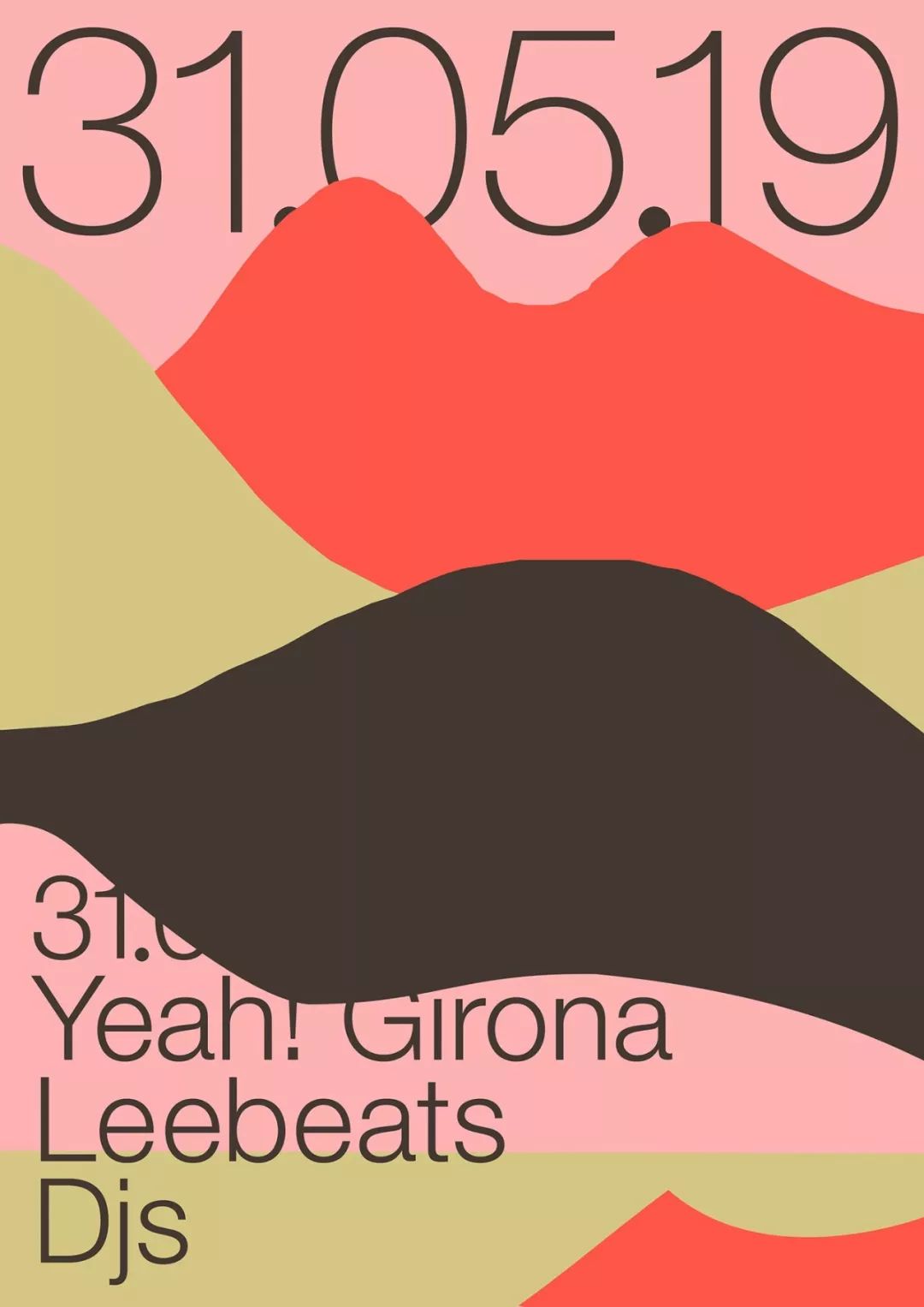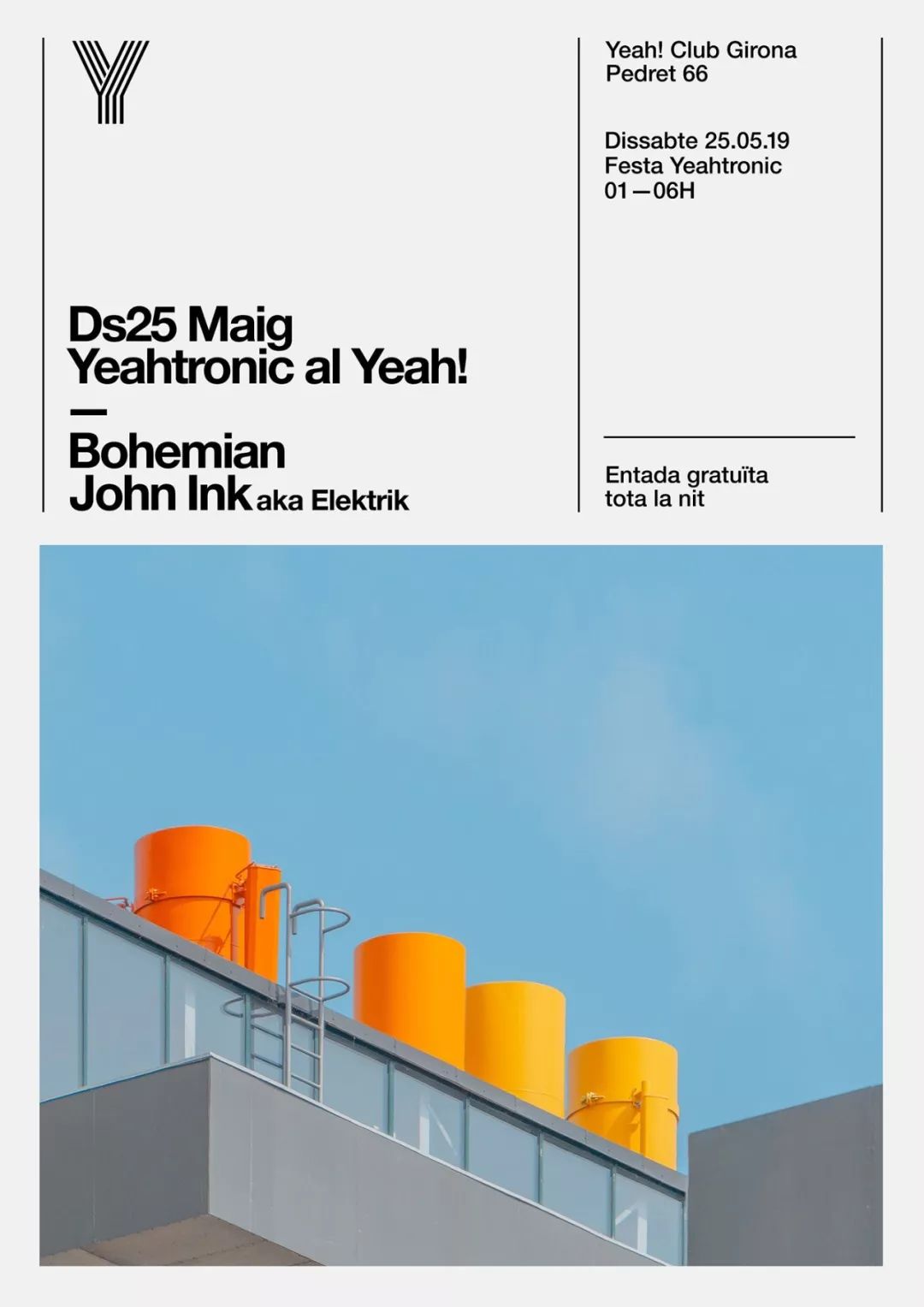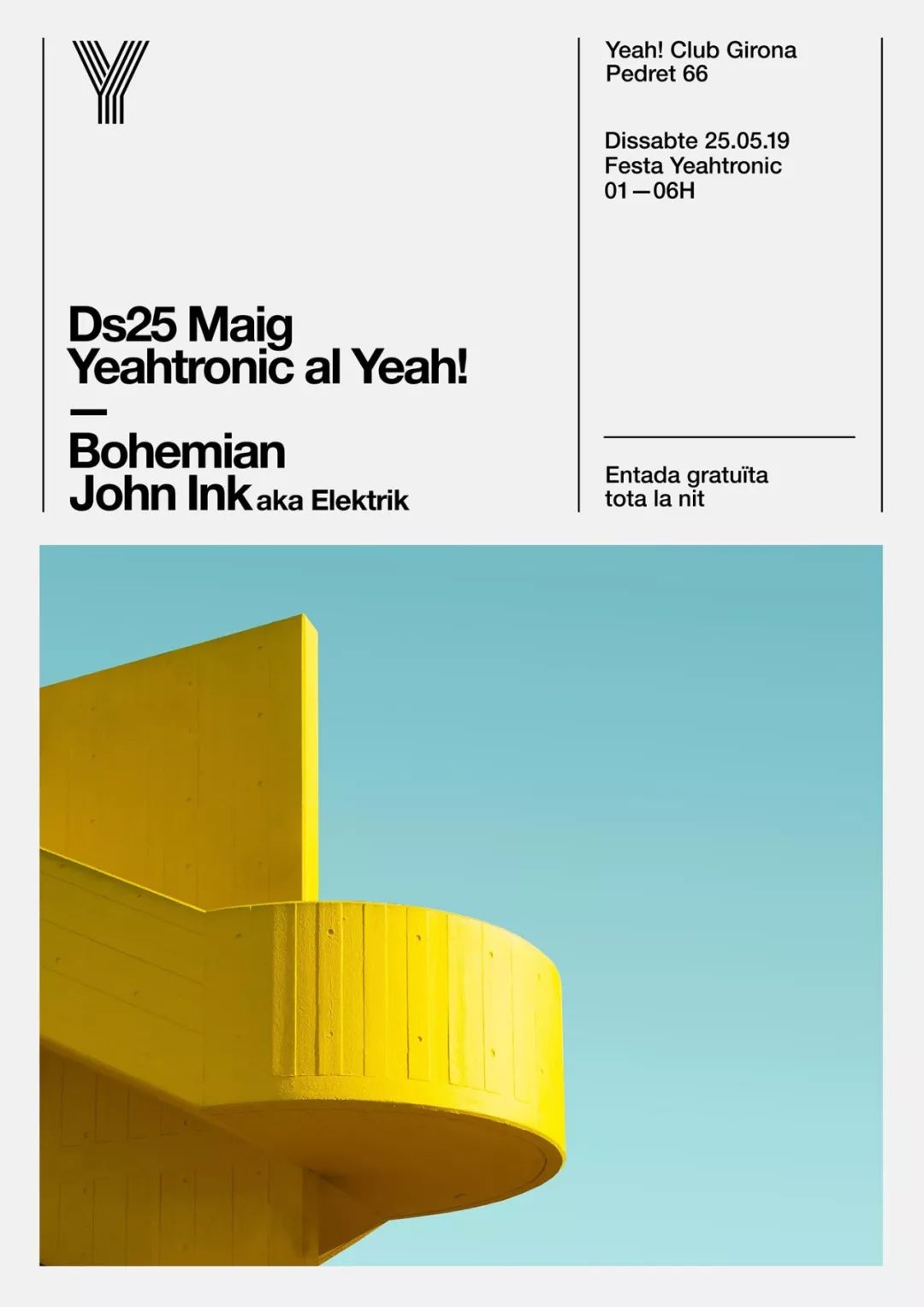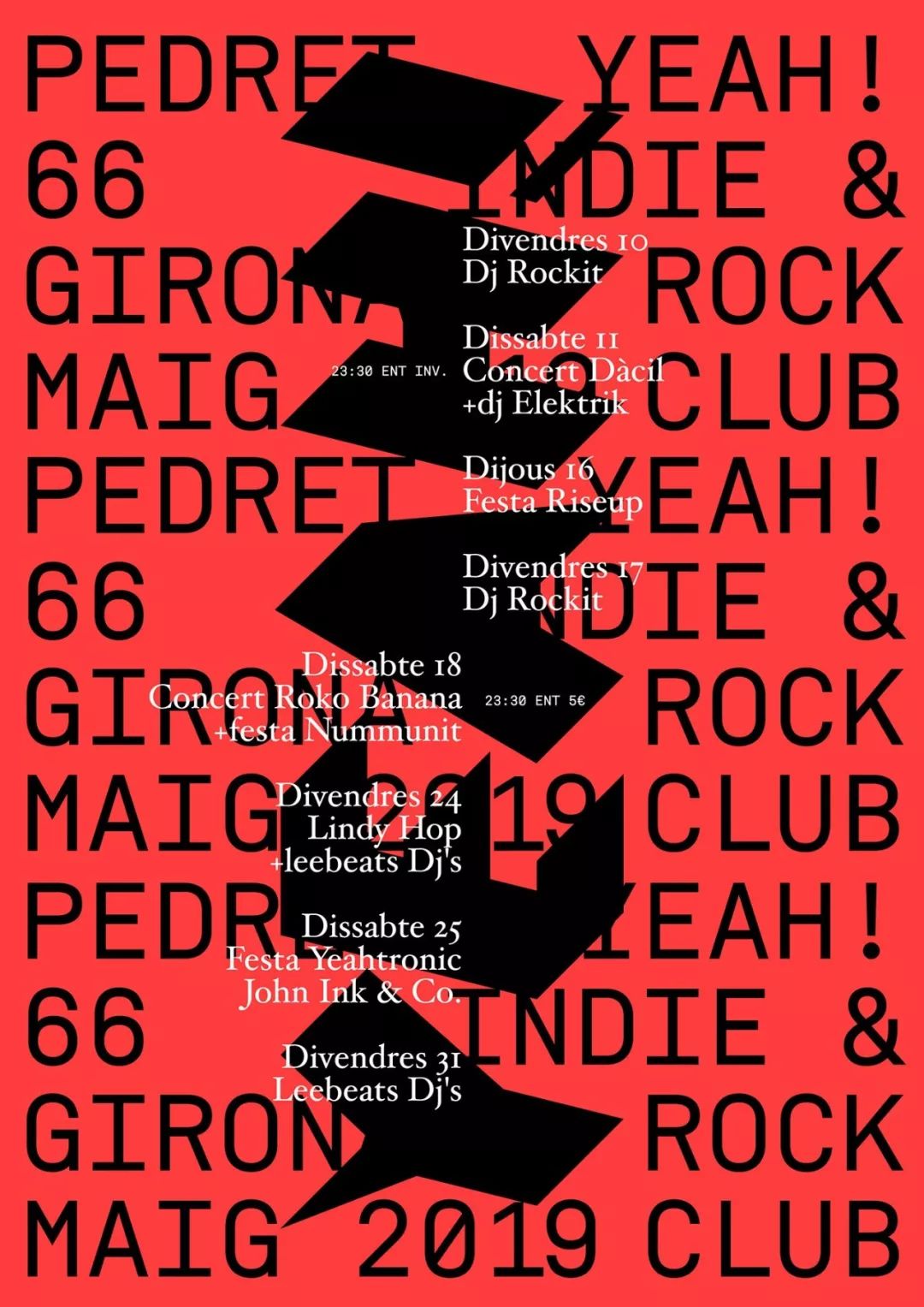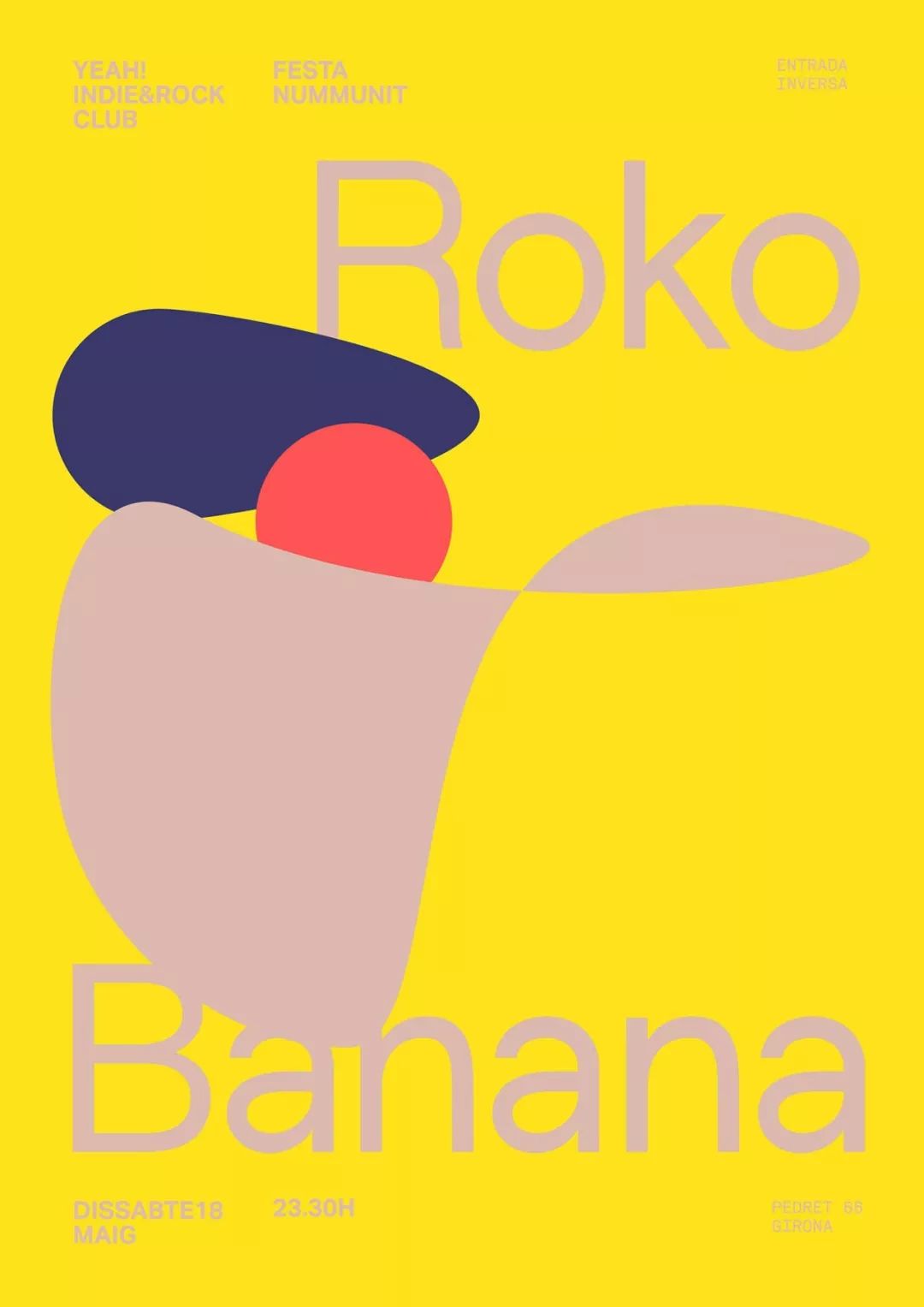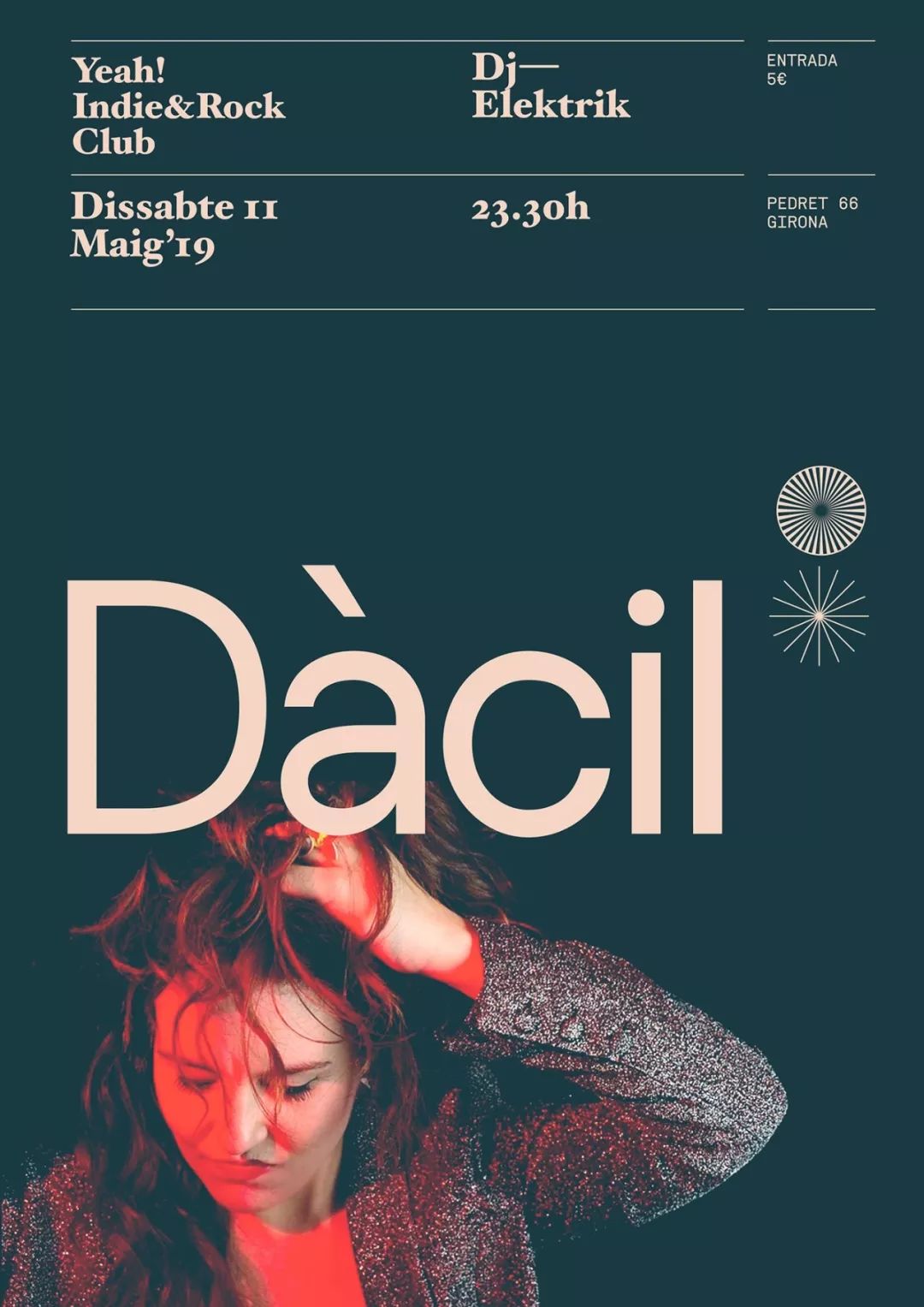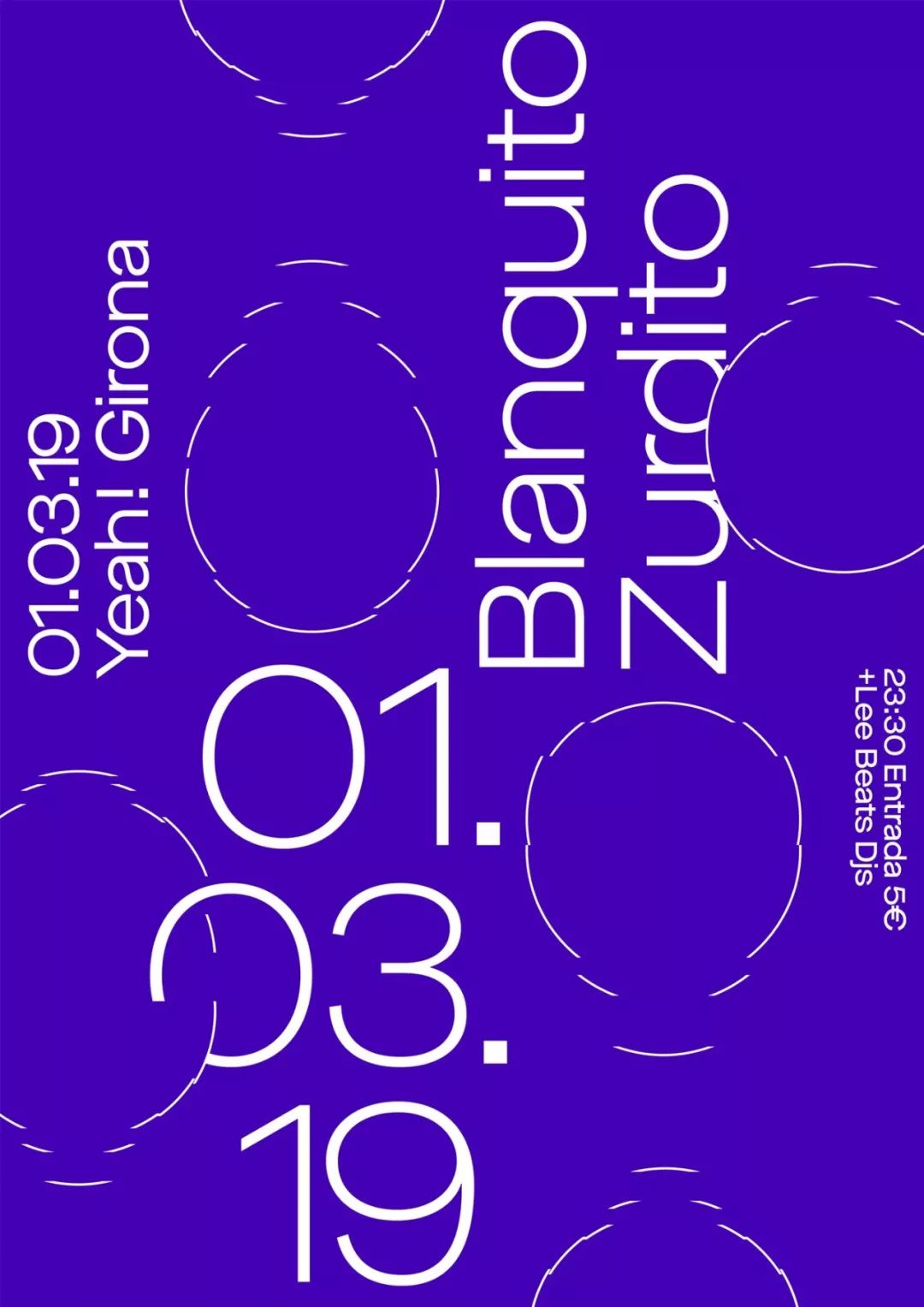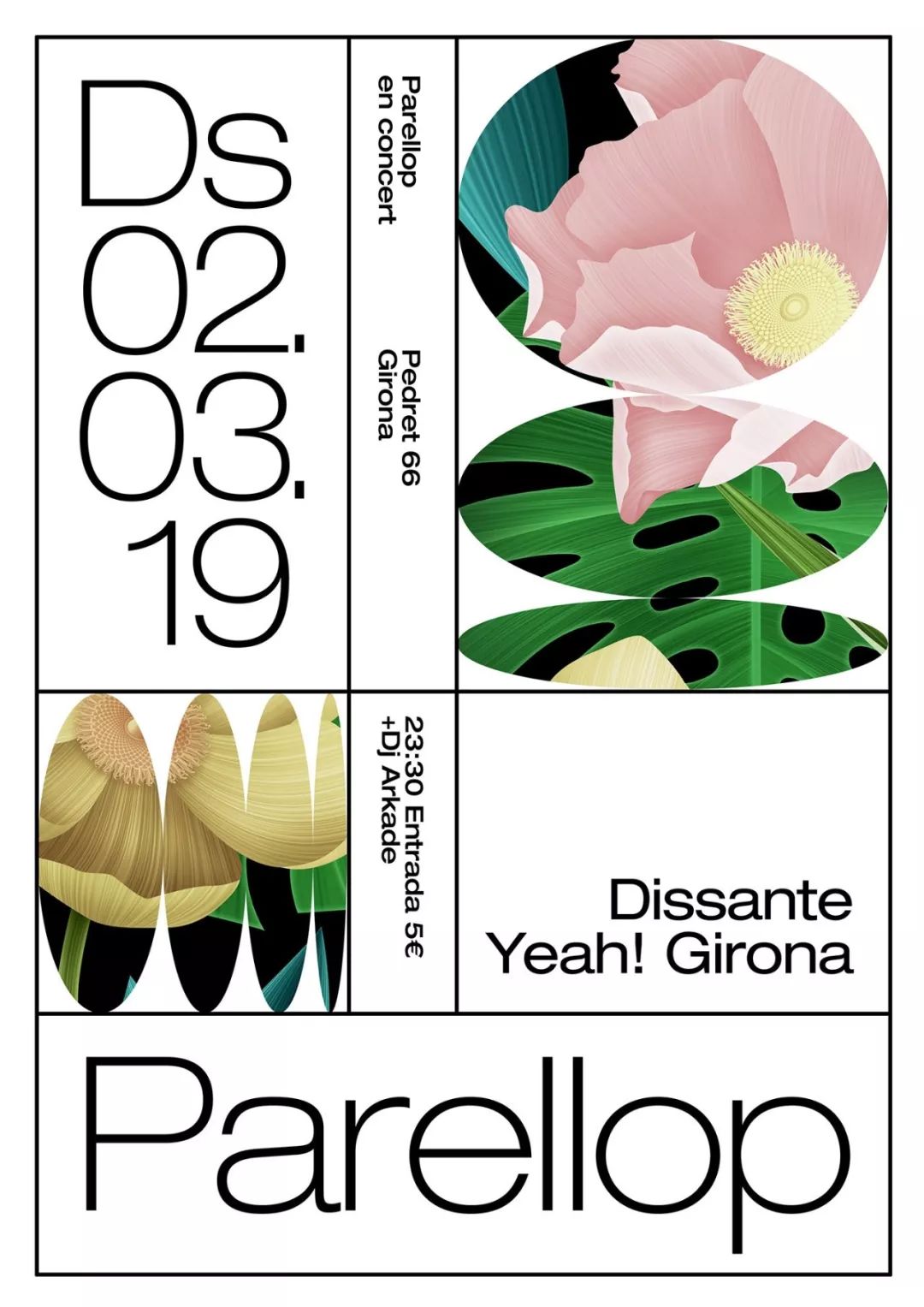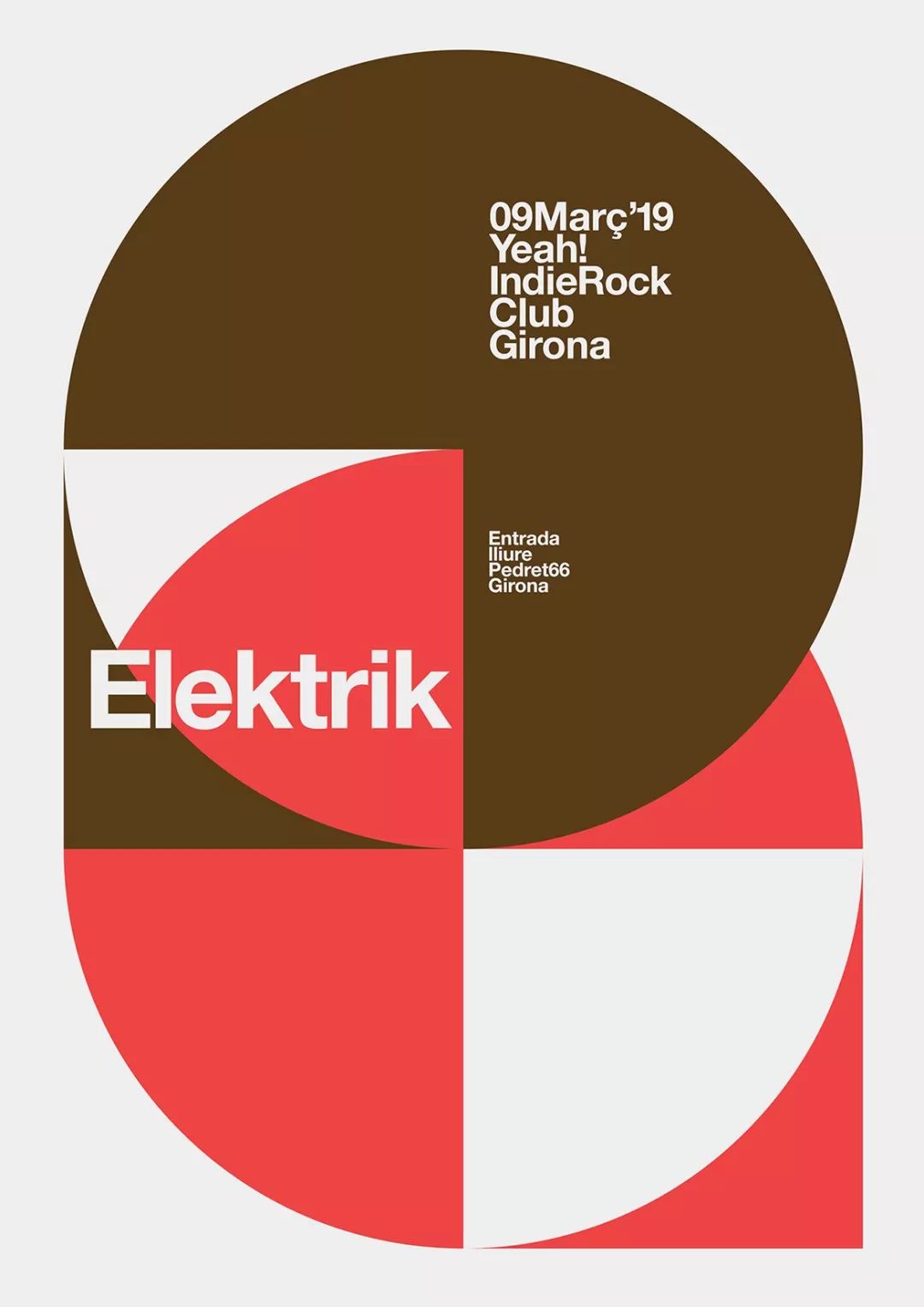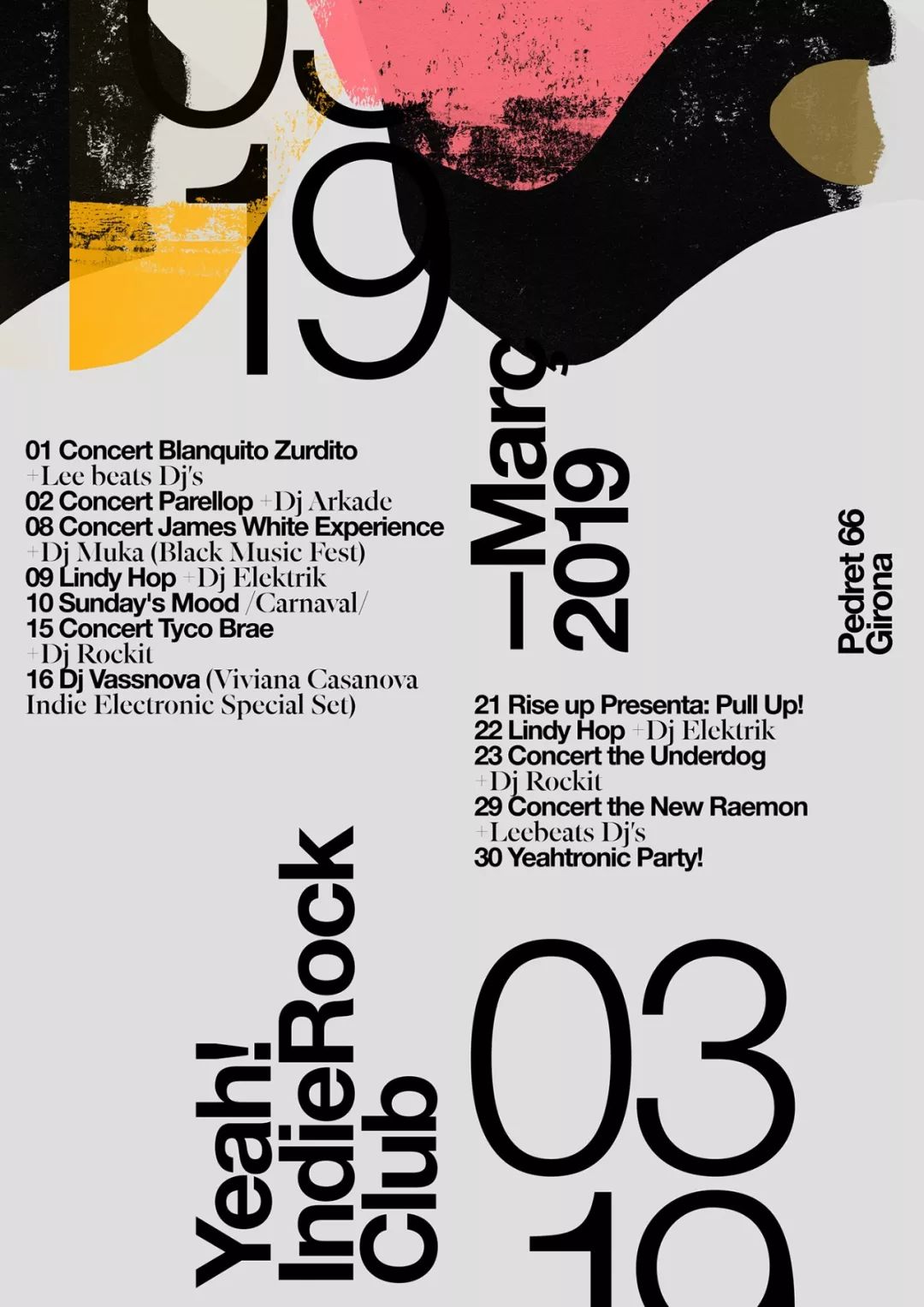
排版怪才 Quim Marin 又发新作品了~
Quim Marin,应该很多人都听过这个名字,他是西班牙巴塞罗那的一位平面设计师,他已经创作了相当多可圈可点的作品,并且每年他都会晒一些他引以为傲的海报设计系列。
他的作品主要通过简单的平面图形来塑造,值得一提的是,他对排版超级在行。他神奇的将各种元素组合体现了他独特的设计风格和技巧。他的风格非常简单,使用形状、颜色和字体,设计出一种全新的、令人难忘的设计,它的目标是在美的均衡,同时确保沟通的有效性。
5月25日,Quim Marin 发布了一组新作品《Poster Collection March/May 2019》,无一不展示了这位怪才设计师对图形图案和排版的独到运用。一共70张图片,一起来看看。
富有创造力、解决方案令人难忘的 Quim Marin,他的视觉语言总是那样一目了然。如果这些还不够满足你的眼球,那么可访问他的网站:www.quimmarin.com